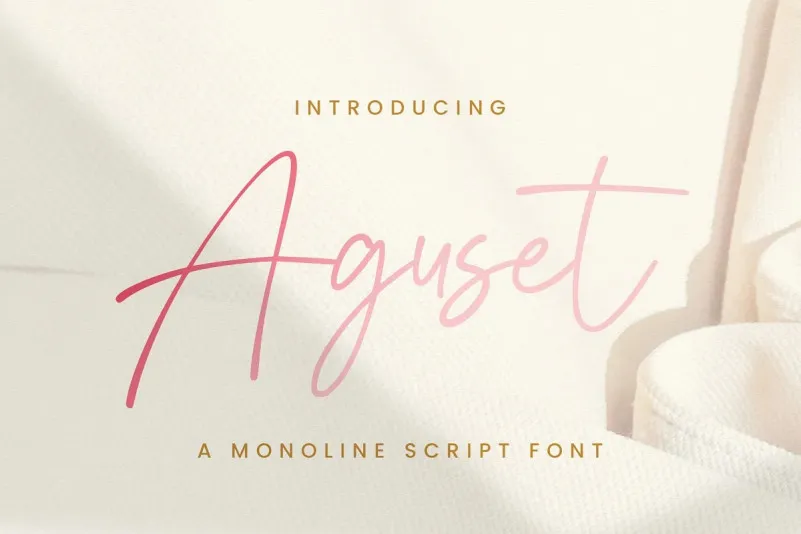
Aguset Script Font – Fonte Grátis
Aguset Script Font
A Aguset Script Font é uma elegante tipografia script casual criada por StringLabs. Com caracteres bonitos e equilibrados, ela se adapta a inúmeros projetos e designs. Se você está buscando um recurso de fontes que adorne seus trabalhos de design com um toque singular e atraente, essa é uma opção perfeita para o seu catálogo. Adicionar Aguset Script Font aos seus trabalhos mais criativos pode fazer eles se movimentarem vivos no seu projeto final. Sua facilidade em combinar-se em uma variedade de contextos design torna-a uma escolha única e versátil, que certamente não decepcionará até mesmo os projetos mais exigentes.